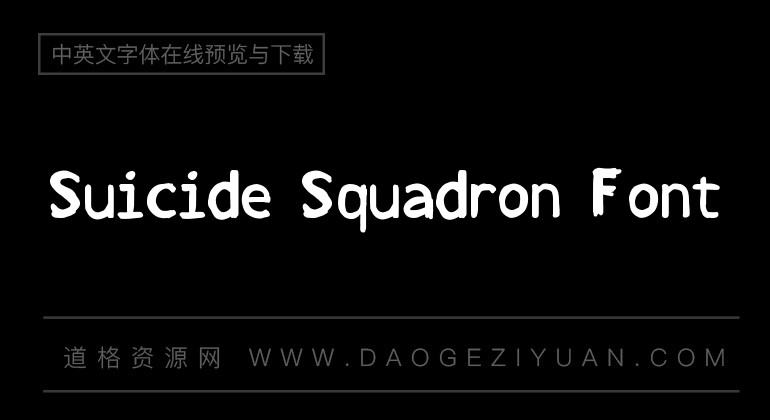
Suicide Squadron Font
Suicide Squadron Font 是一款由 Blambot 制作的免费字体,其设计灵感来源于二战时期的美国空军涂鸦艺术。 该字体的特点在于其具有粗犷、有力的笔划,带有一定的草率感,呈现出一种军队和战争的氛围。它包括了大写字母、数字和一些符号,可以用于制作海报、标志、漫画和其他设计项目。 Suicide Squadron Font 虽然有些粗糙,但也是一款非常实用的字体,适合于需要表现出强烈、坚定和决绝的设计项目。
Suicide Squadron Font是一款非常不错的手写艺术字体,具有很好的视觉感,适合于文化类的宣传设计、商业类品牌的广告和产品包装设计以及个性化文字排版等较多场景。